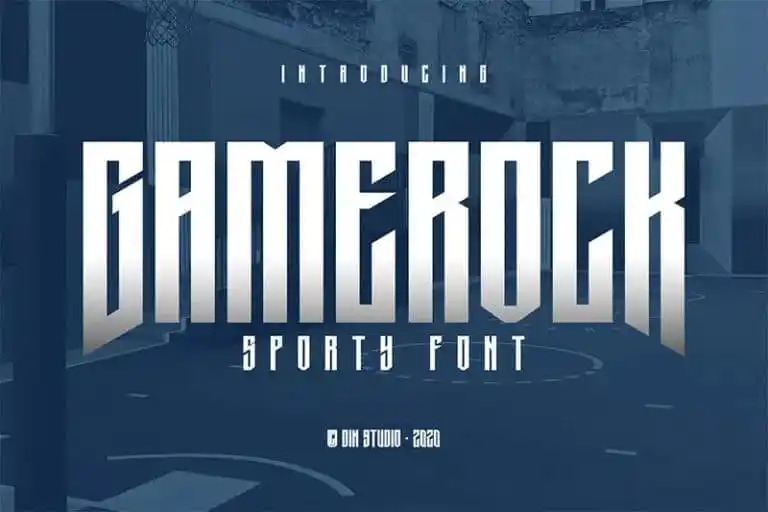
Gamerock Display Font – Download Grátis
Introduzimos Gamerock Display Font, uma fonte tipo-display versátil com caracteres descontraídos. Este tipo de fonte é claramente inspirada na estética dos esportes e foi criado pelo Din Studio. Além de ser ideal para projetos profissionais relacionados a esportes, essa fonte também se destaca como uma opção perfeita para impressão, criação de marca e citações. Seja para criar materiais promocionais de jogos ou para personalizar suas próprias mensagens com estilo, Gamerock Display Font é certamente uma ótima escolha. Engloba a essência desportiva em cada letra, tornando-a um recurso gráfico versátil e encantador.